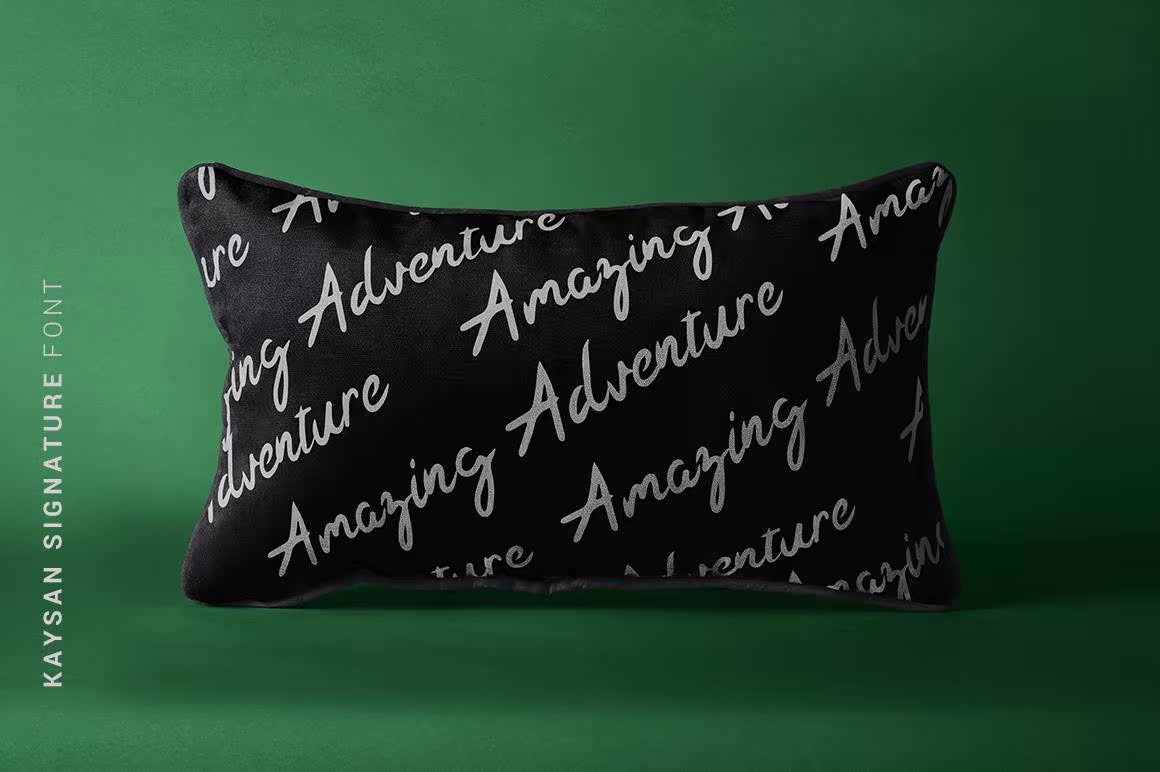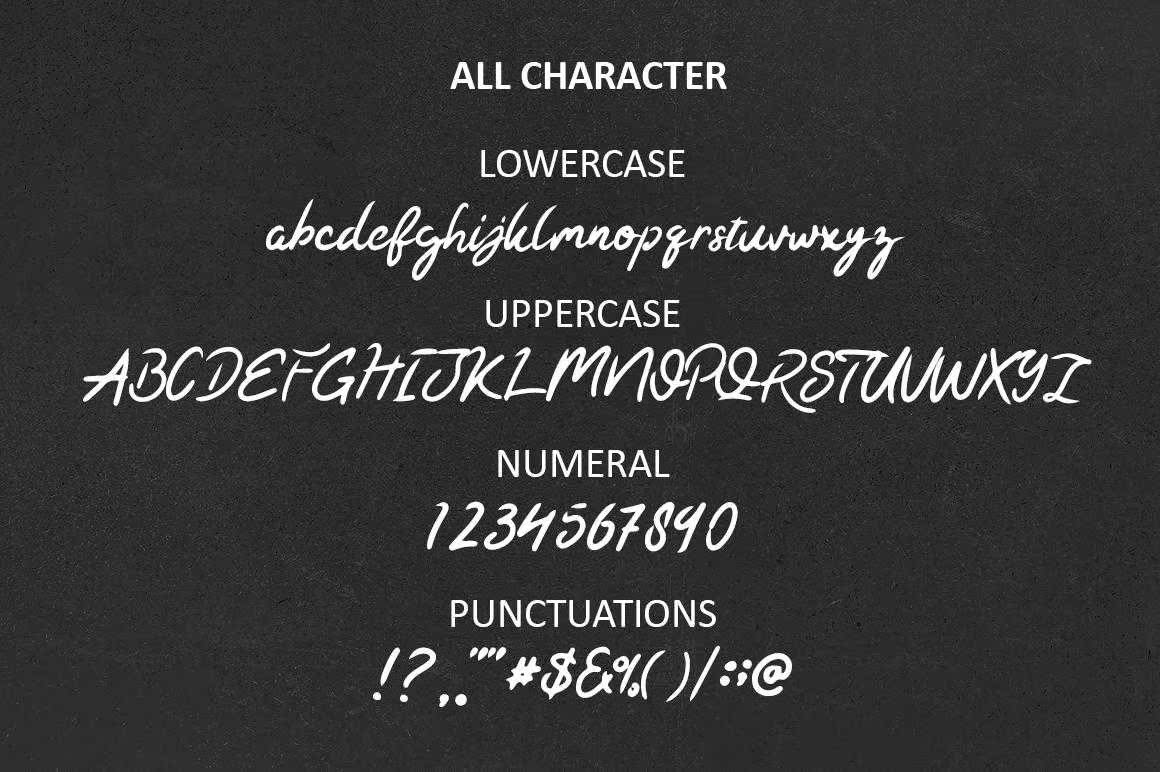
介绍Kaysan签名,A和WritteneLegantScriptFont!这种大胆、自由流动、充满自信的画笔风格设计简单。Kaysan签名是一种您可以使用并再次获得的画笔,用于从促销材料和书面报价到产品包装、商品和品牌项目的任何内容。介绍Kaysan签名、A和书面Legant脚本字体!这种大胆、自由流动、充满自信的画笔风格设计简单。Kaysan签名,您可以使用它并再次获得,用于从促销材料和书面报价到产品包装、商品和品牌项目的任何内容。